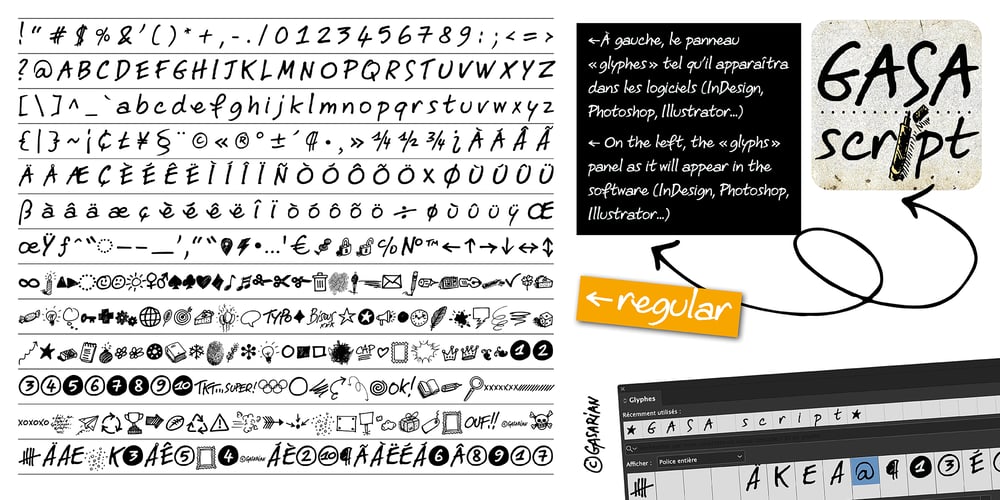
Gasa Script Reg Font Family was designed by Christine Gasarian and published by Gasarian. Gasa Script Reg contains 2 styles and family package options. Gasa Script est une police “faite main”, d’après ma propre écriture manuscrite. Elle permet d’ajouter une touche manuscrite à n’importe quel projet. On peut associer la police avec des Dingbats, pour créer des rébus par exemple.N’hésitez pas à vectoriser les 89 dingbats (très imagés) pour jouer avec, et un conseil, gardez toujours la palette “glyphes” ouverte. Et si vous ne trouvez pas votre bonheur parmi ces Dingbats, je peux en dessiner sur commande !